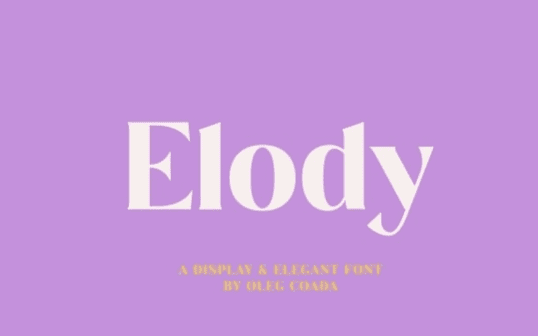
[Creativemarket] Elody Display and Elegant Font (2021)
Название: Elody Display and Elegant Font (2021)
[Creativemarket] Elody Display and Elegant Font (2021)
Новый шрифт Elody - это дисплейный и элегантный шрифт с засечками, идеально подходящий для брендинговых проектов, заголовков, постеров и упаковки!